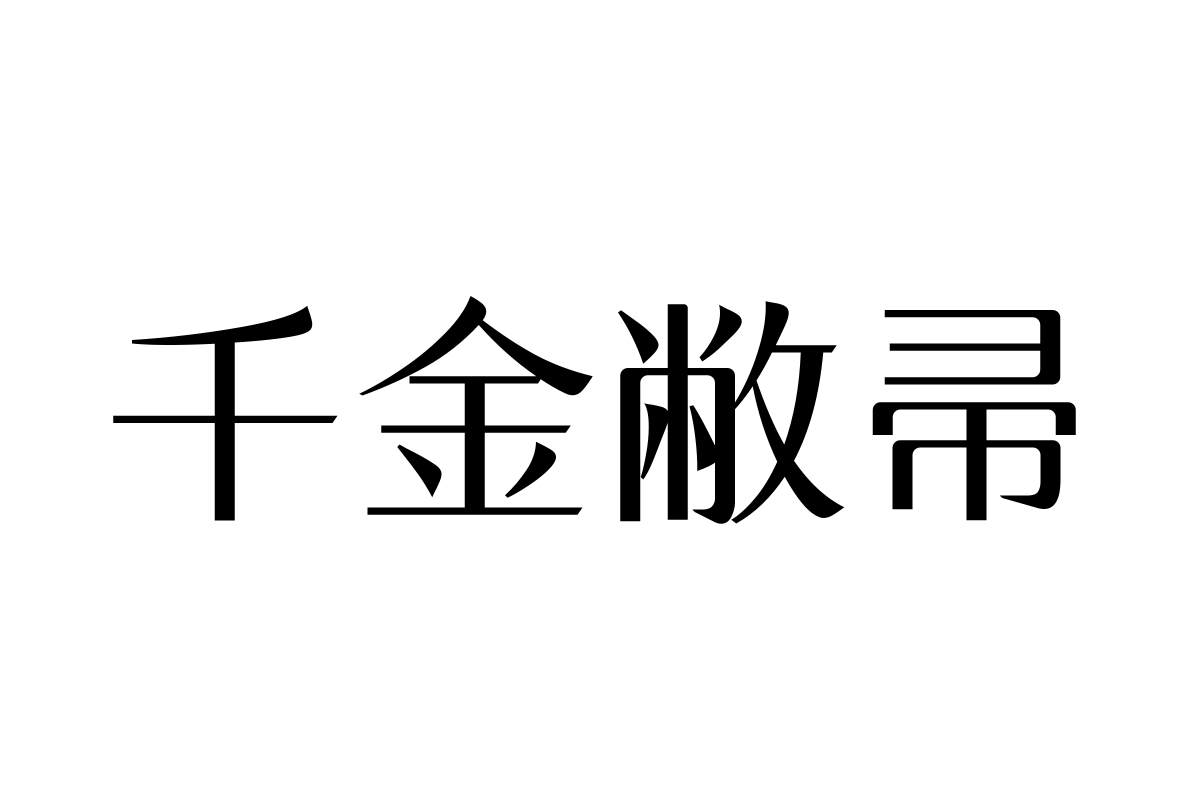
三极博宋是一套由台湾三极科技公司开发的简体中文字体。它以其独特的风格和设计,在简体中文字体市场中占有一席之地。以下是对三极博宋字体的一些介绍:
1. 设计风格:三极博宋采用了一种简洁、现代的设计风格,字母和字形线条流畅,整体感觉清爽。这种设计风格使得它在阅读和书写时更加舒适,同时也适合用于各种印刷品和数字媒体。
2. 字体特点:三极博宋的字体特点主要体现在其笔画的粗细变化上。它的笔画粗细适中,既不过于粗犷,也不过于纤细,这使得它在视觉上给人一种平衡感。此外,三极博宋还具有一定的装饰性,如一些字母的尾部会稍微加长,形成一种独特的视觉效果。
3. 适用场景:三极博宋适用于各种需要使用简体中文的场合,如书籍、杂志、报纸、广告、网页等。同时,它也适合用于电子出版物,如电子书、手机应用等。
总的来说,三极博宋是一款具有独特风格的简体中文字体,无论是从设计风格还是字体特点上,都展现出了很高的水平。如果你需要一款简约而现代的简体中文字体,三极博宋绝对是一个不错的选择。